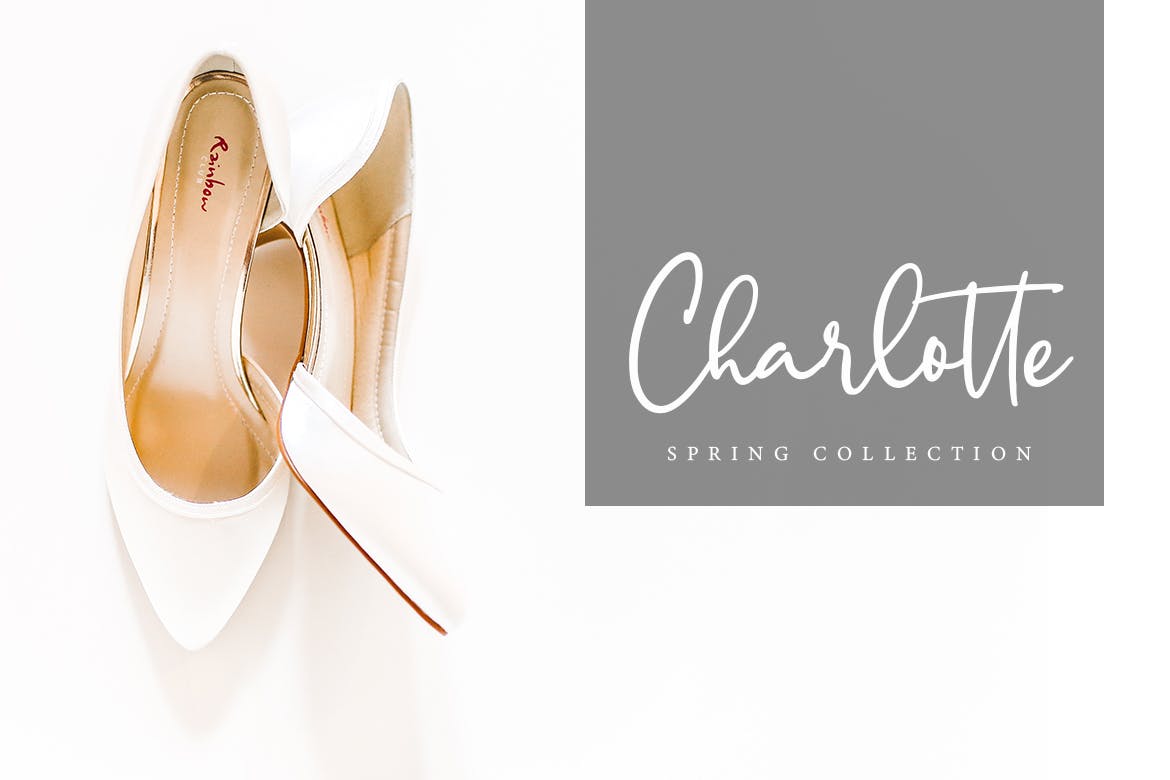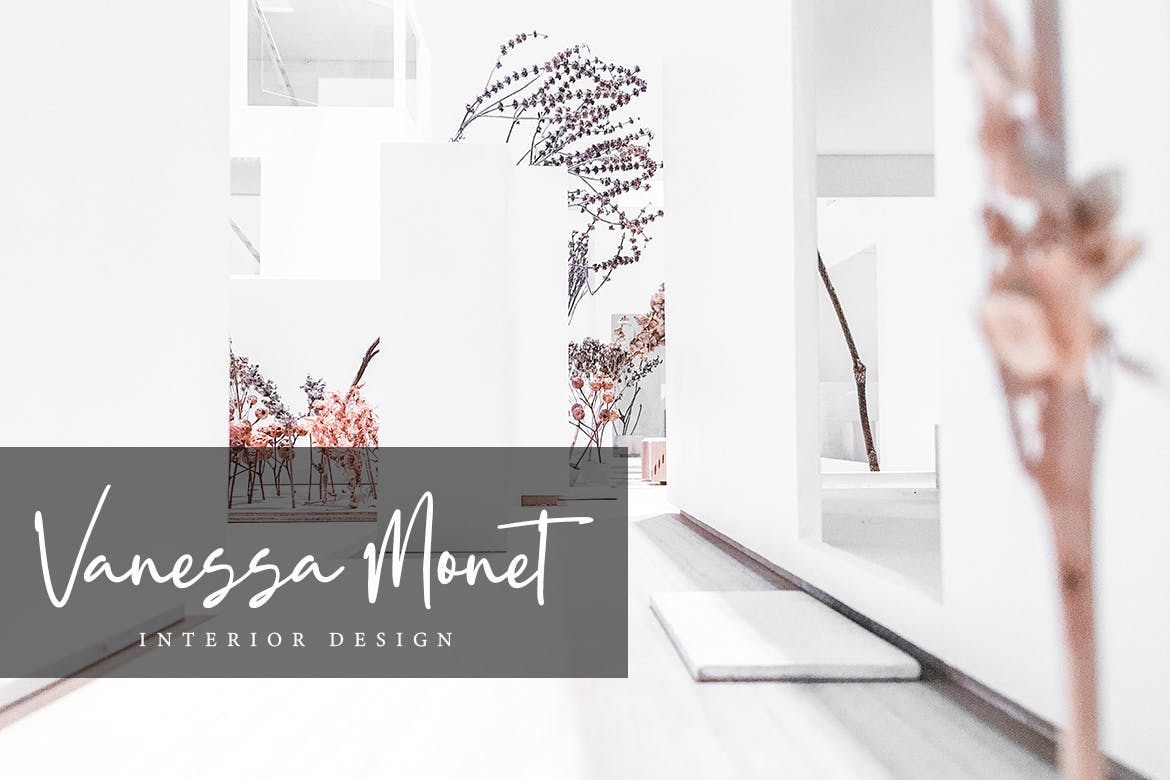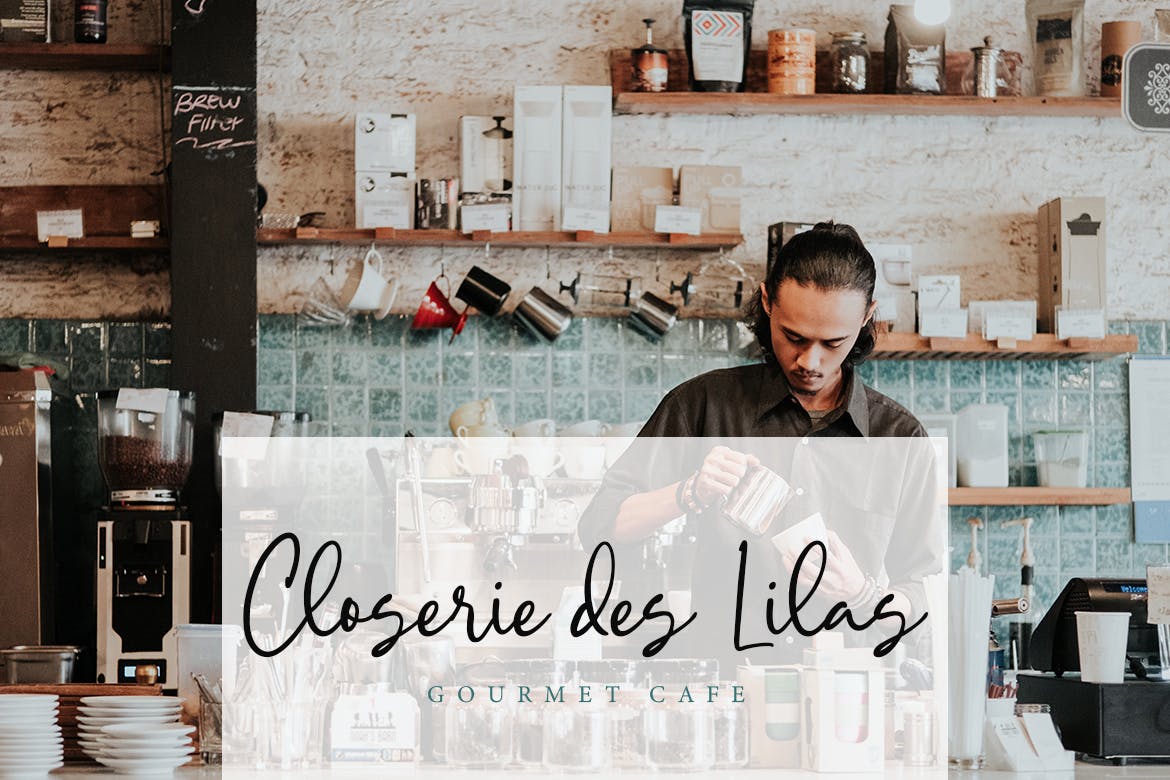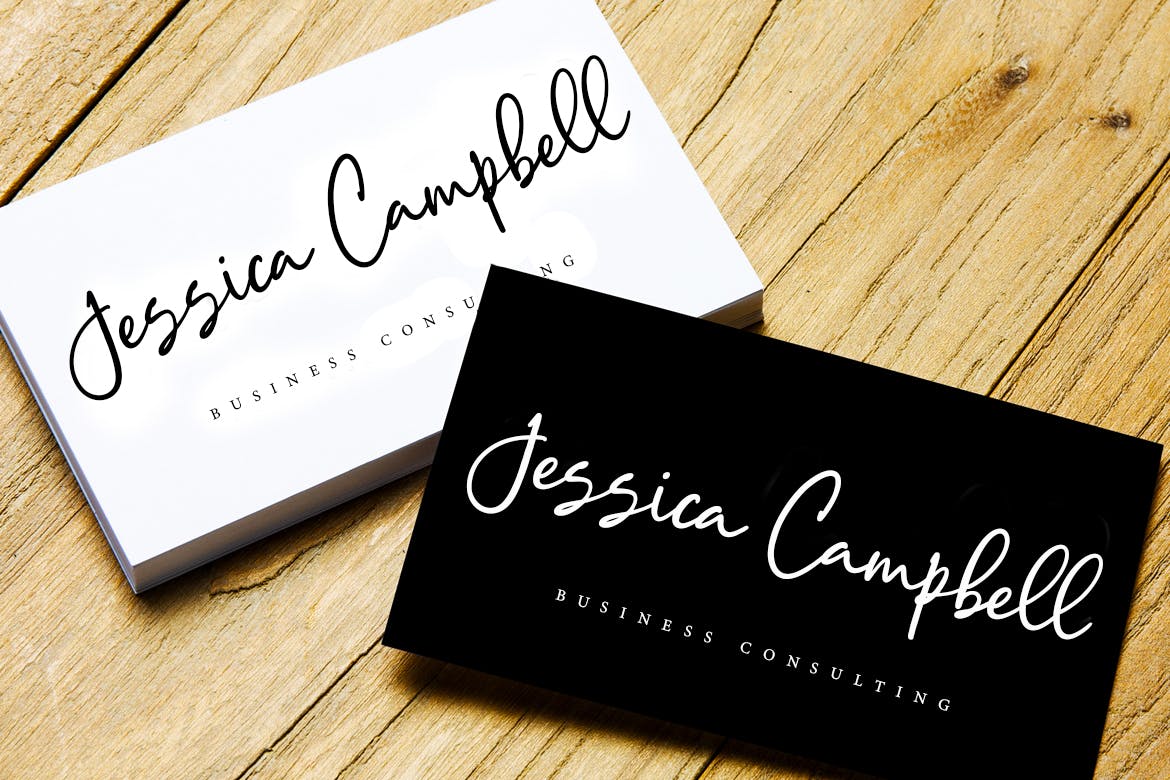
Estrela Luxury Wedding Font
فونت Estrela، انتخابی ایده‌آل برای طراحی‌های لوکس و خاص.
Estrela یک فونت دست‌نویس با سبک امضای لوکس است که پروژه‌های شما را فوق‌العاده می‌کند.
Estrela برای پروژه‌های برندینگ، لوگو، طراحی‌های عروسی، پست‌های شبکه‌های اجتماعی، تبلیغات، بسته‌بندی محصولات، طراحی محصولات، برچسب، عکاسی، واترمارک، دعوت‌نامه، لوازم‌التحریر و هر پروژه‌ای که نیاز به حس دست‌نویسی دارد، مناسب است.
• گلیف‌های استاندارد
• لیگاتور
• کاراکترهای کدگذاری شده PUA - به‌طور کامل بدون نیاز به نرم‌افزار طراحی اضافی قابل دسترسی است.
• فونت‌ها شامل پشتیبانی چندزبانه برای ä ö ü Ä Ö Ü ß ¿ ¡ می‌باشد.